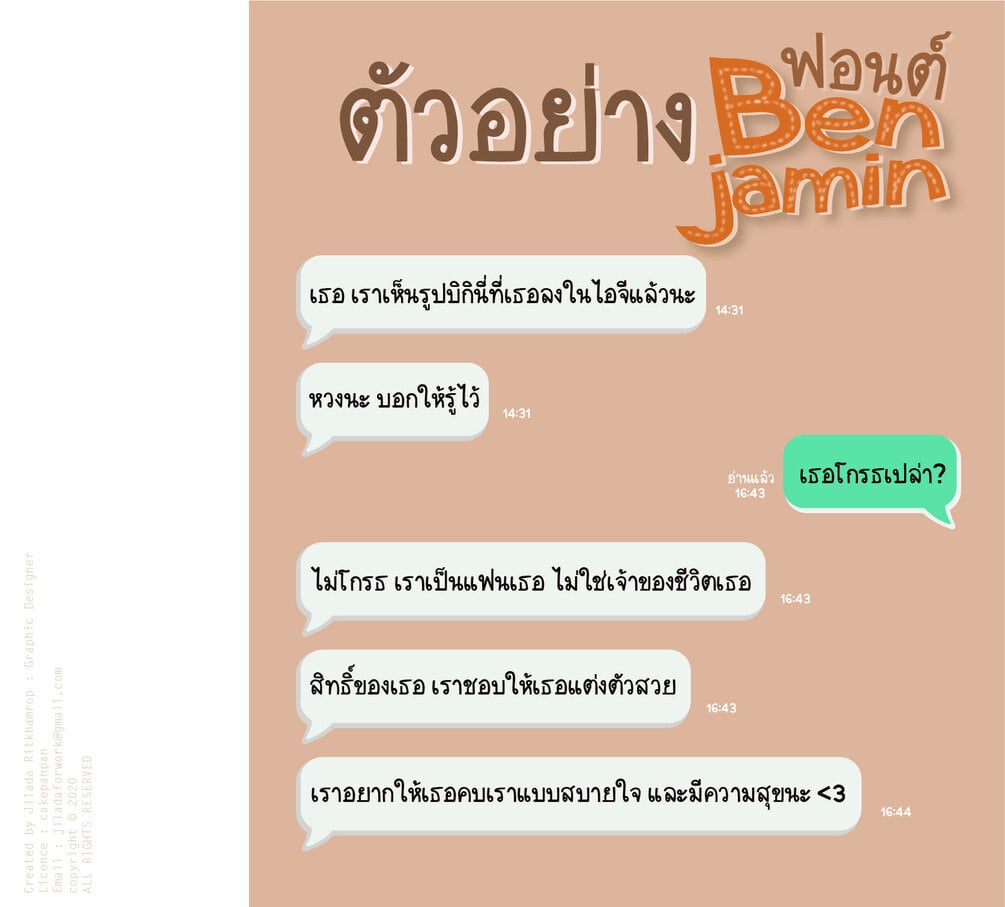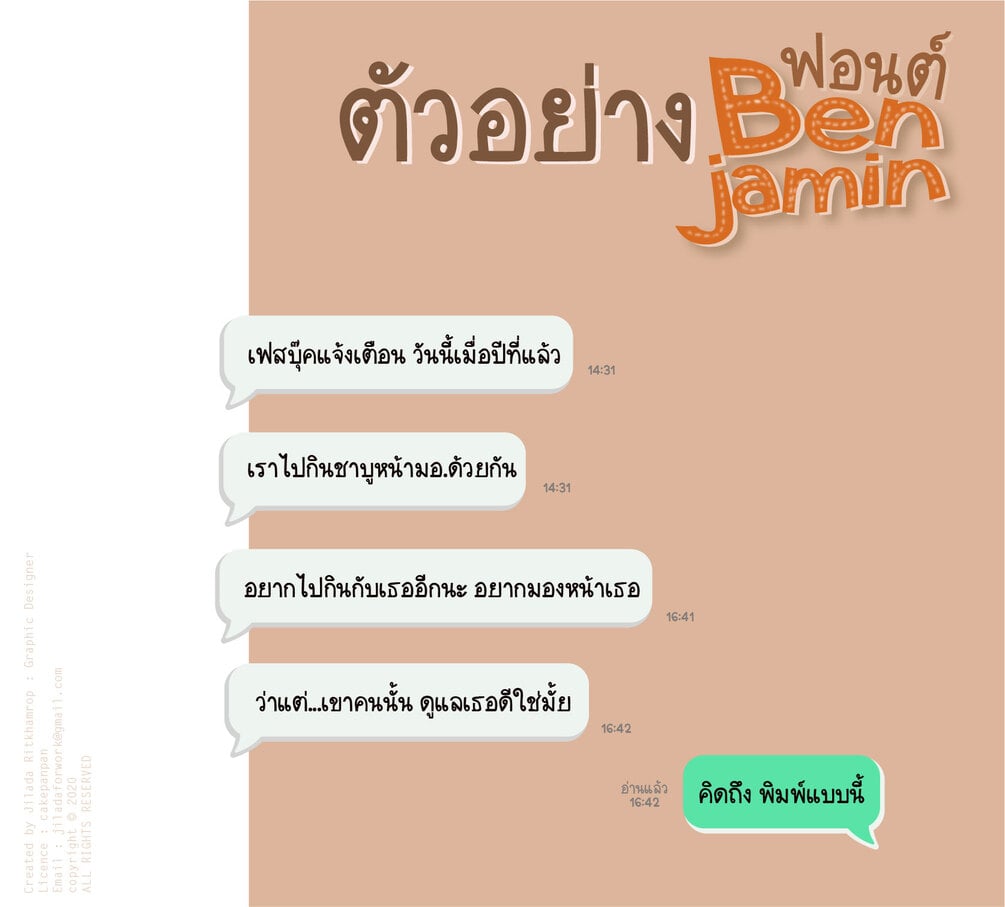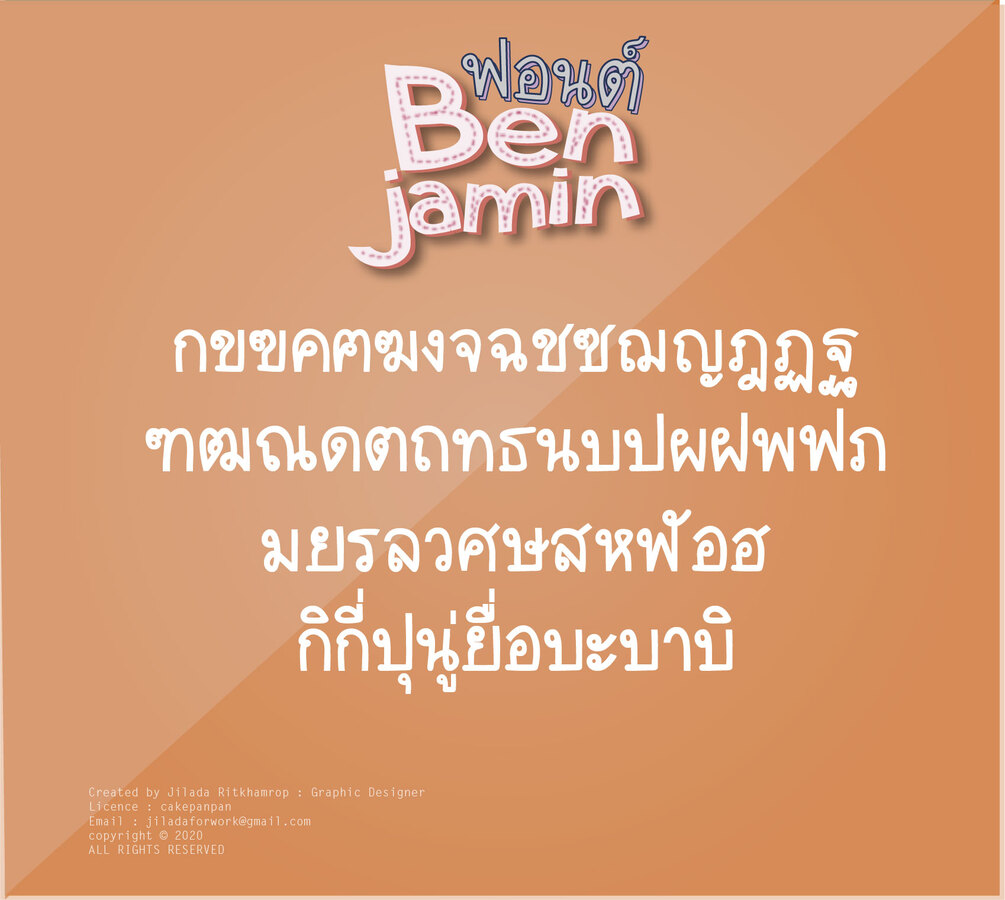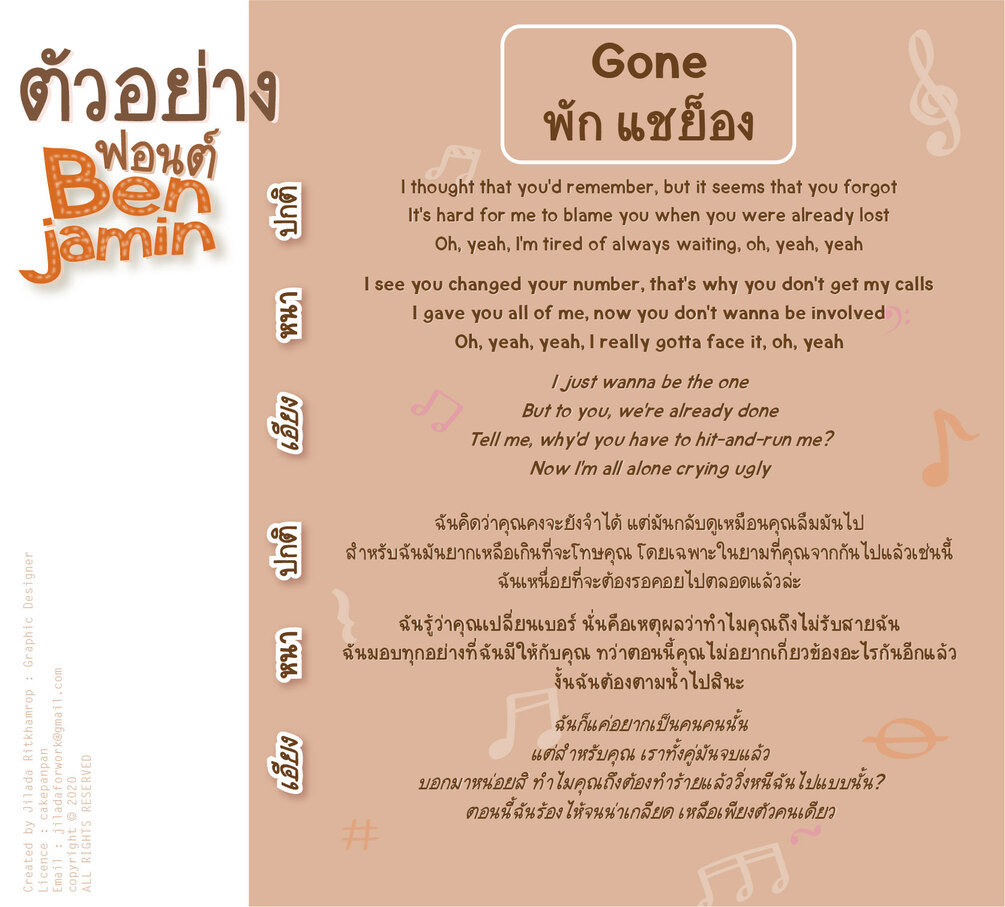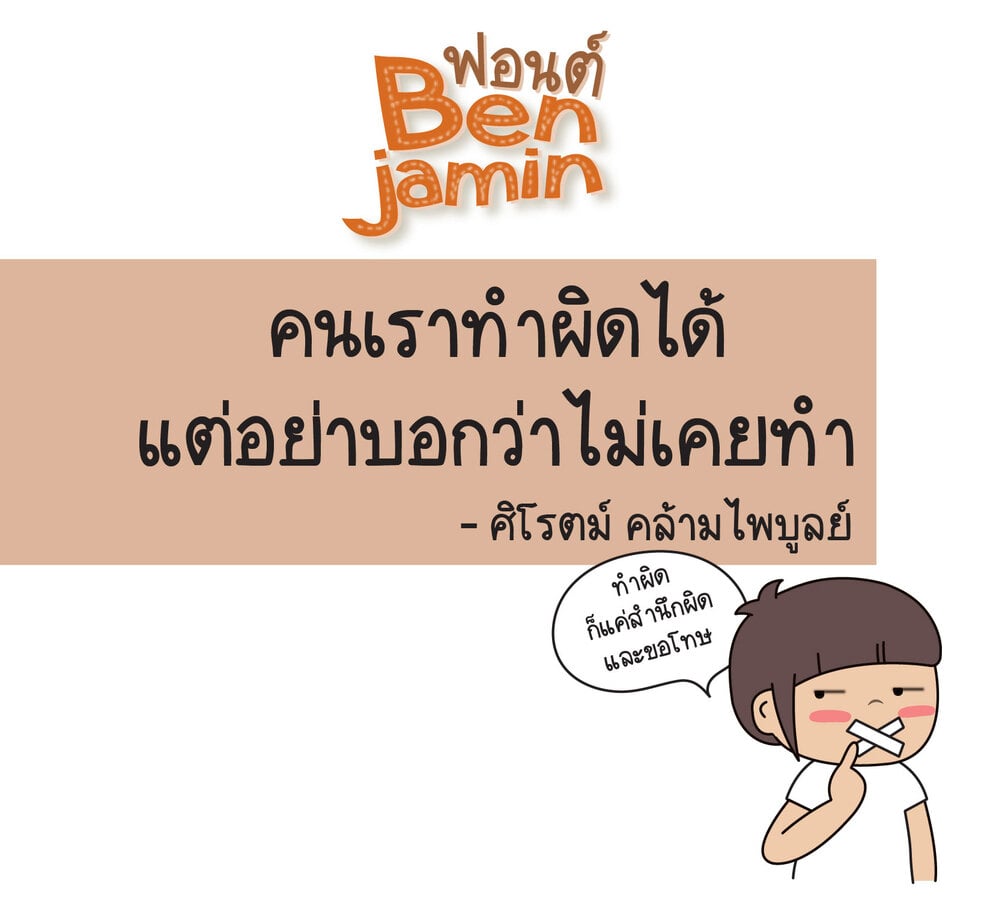
Benjamin Font (ฟอนต์เบนจามิน)
ฟอนต์ลายมือสุดเรียบร้อยดั่งผ้าพับไว้ เบนจามิน!
เหมาะกับนักเรียนนักศึกษาสุดๆ มีทั้งไทยและอังกฤษ 3 น้ำหนัก (หนา ปกติ เอียง)